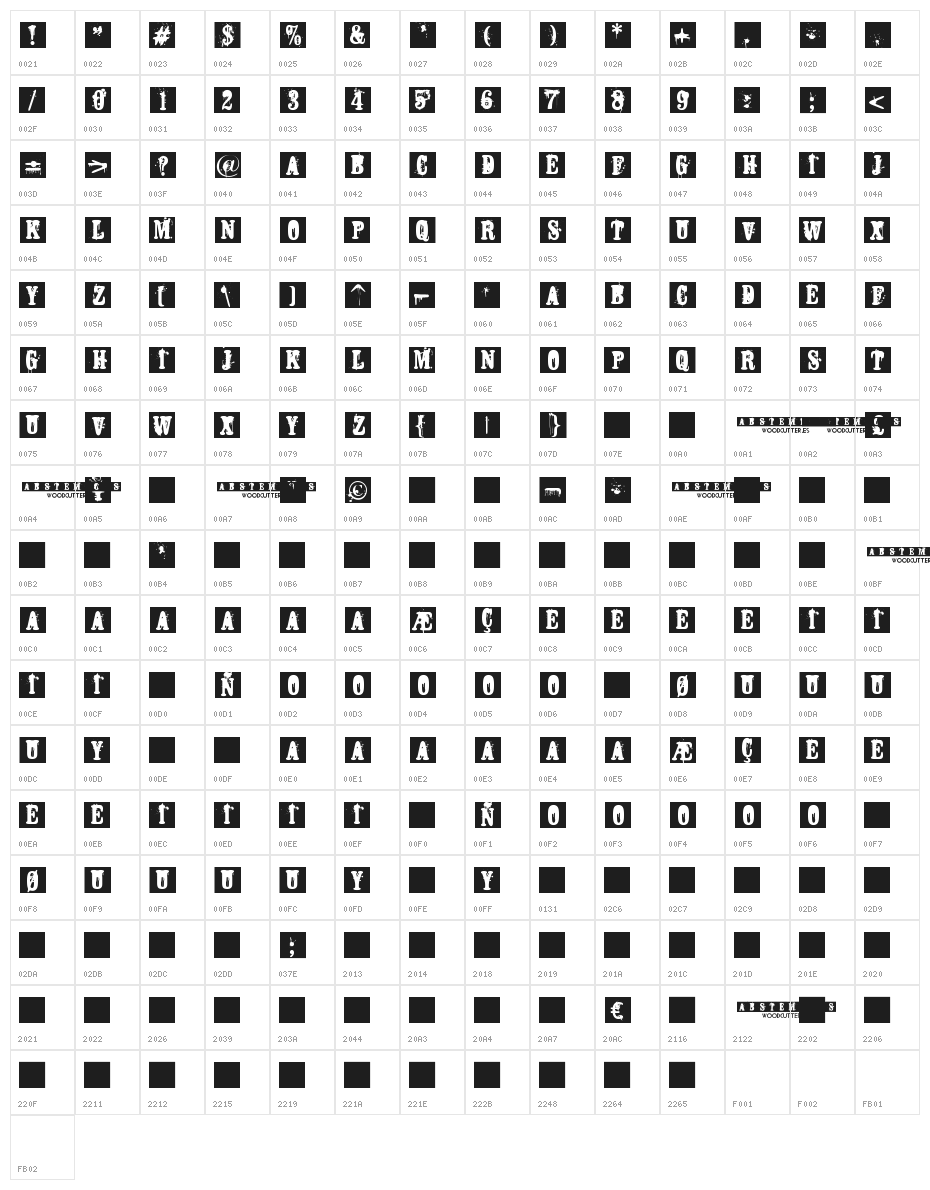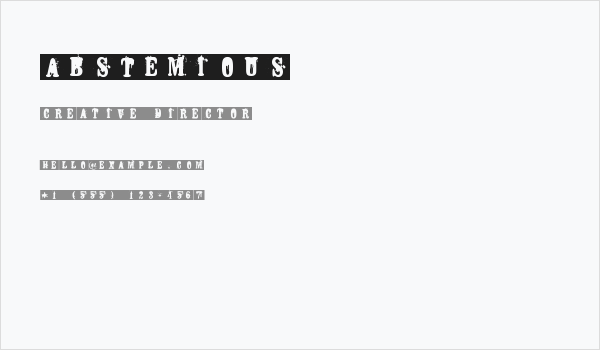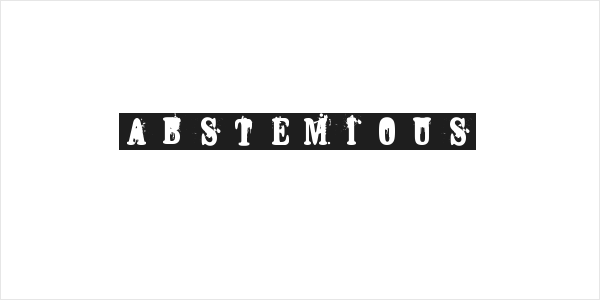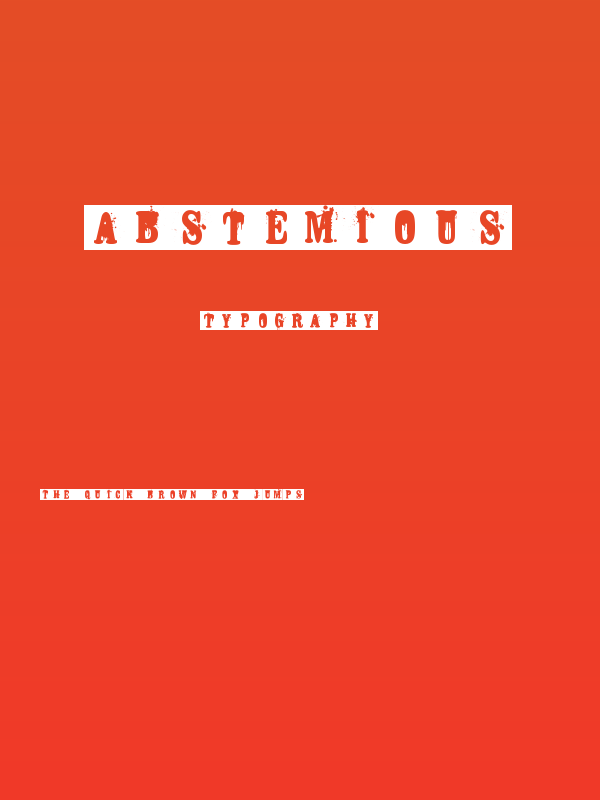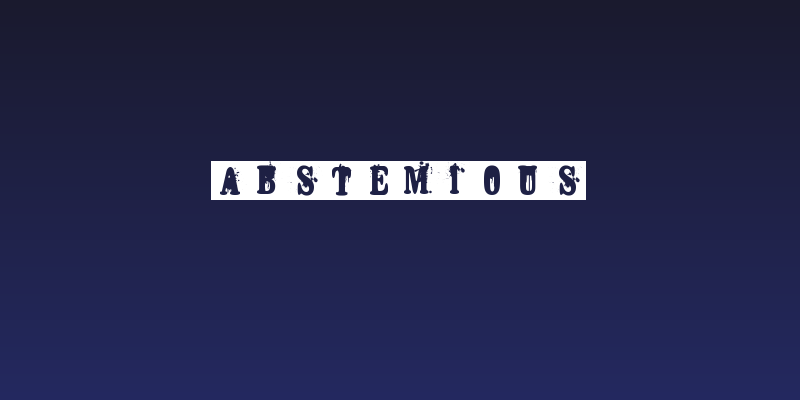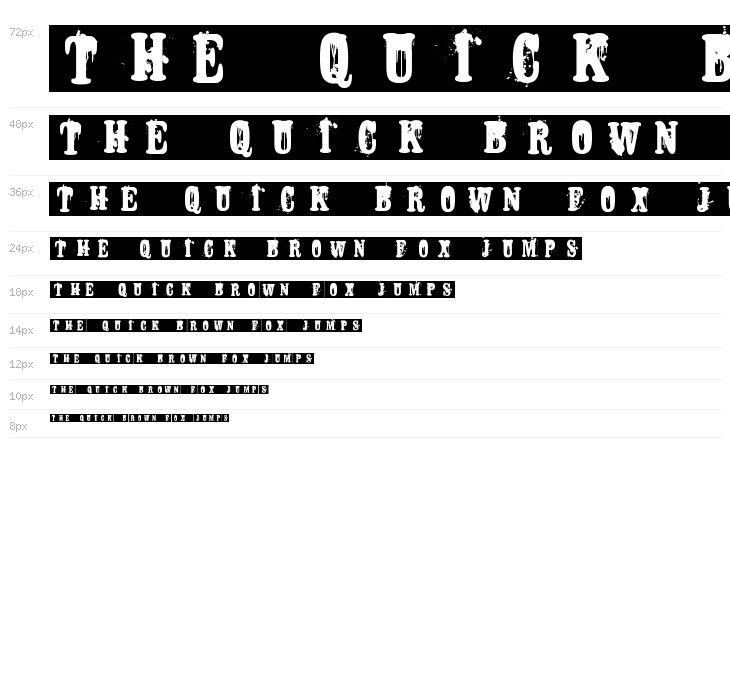
ABSTEMIOUS Font
| Progetti proposti | Ideal for projects requiring a vintage or rugged look, such as posters, album covers, or branding for outdoor or adventure-themed products. |